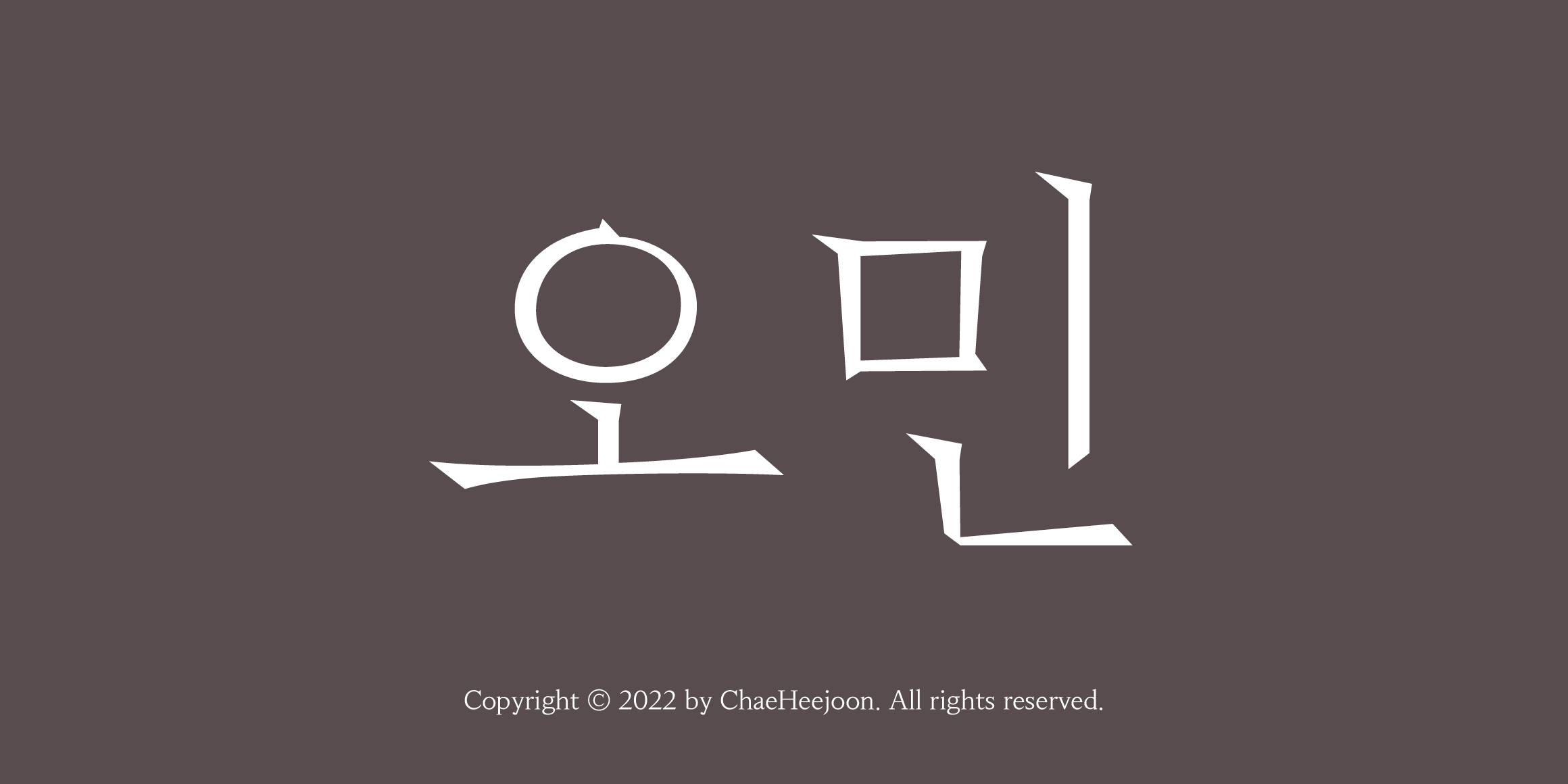
오민
ChaeHeeJoon
분류 Serif,부리
«오민»은 작가 오민을 위해 채희준이 제작한 서체이다. 일민미술관의 주관으로 2022년 오민의 개인전 《노래해야 한다면 나는 당신의 혁명에 참여하지 않겠습니다》의 전시 아이덴티티를 위하여 개발되었으며, 채희준 폰트샵에서 ‘Light’ 웨이트가 정식 출시되었다.
• 한글 2,500자 / 라틴 52자 / 부호 375자
• 오민 / Ohmin